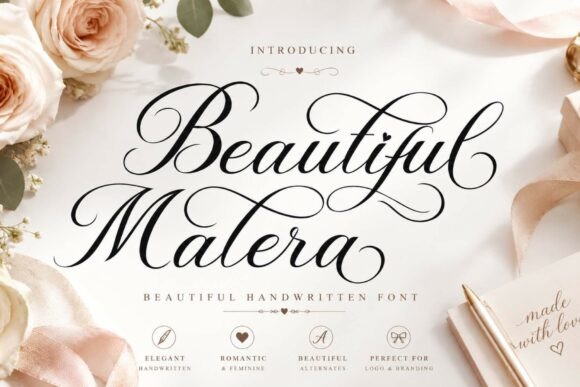
Beautiful Malera
適切なデザイン要素を見つけるのは難しい場合がありますが、Beautiful Maleraは作品を即座に引き立てる優れたコレクションを提供します。
POD(オンデマンド印刷)製品、結婚式の招待状、またはソーシャルメディアのグラフィックを作成している場合でも、Beautiful Maleraは理想的です。